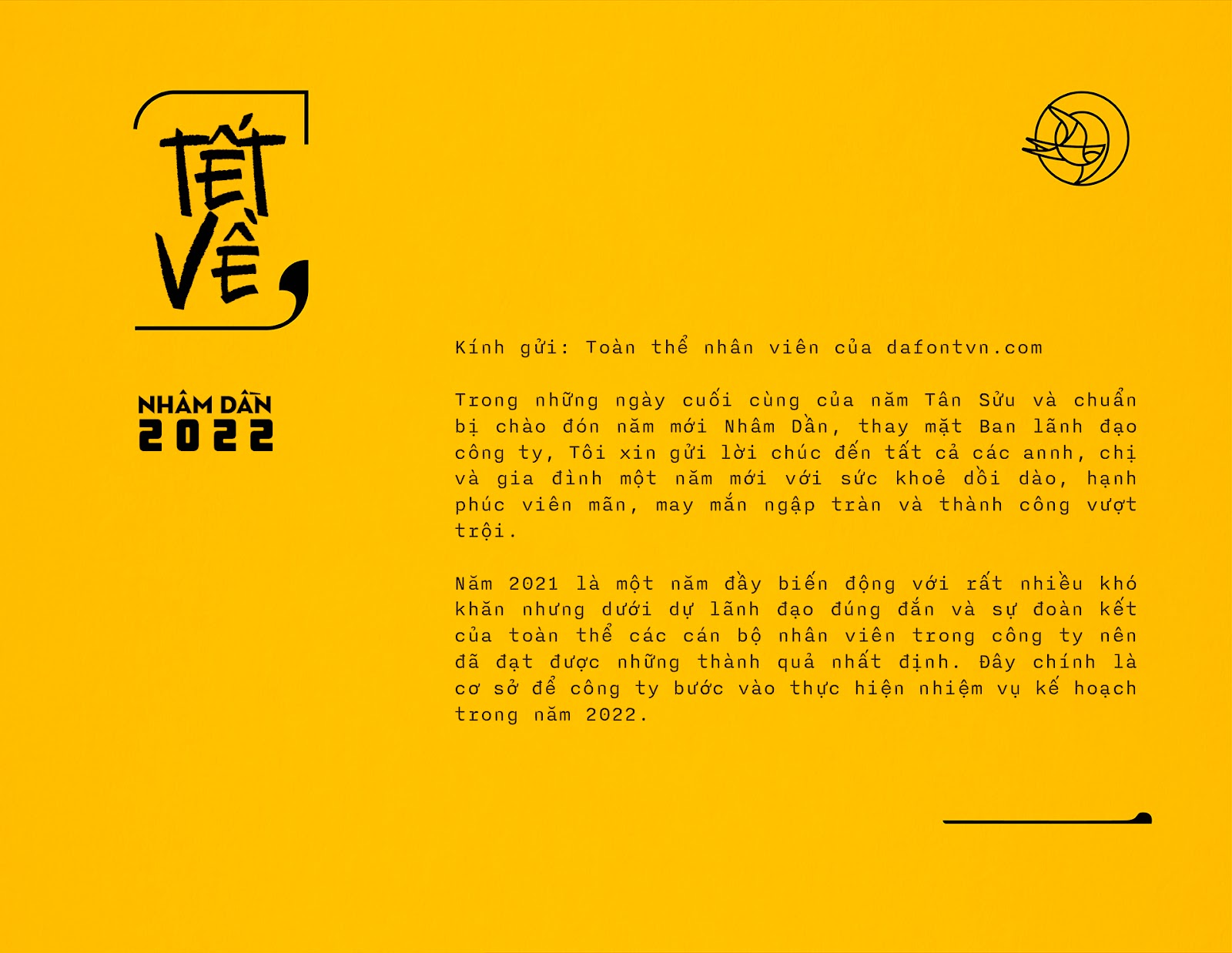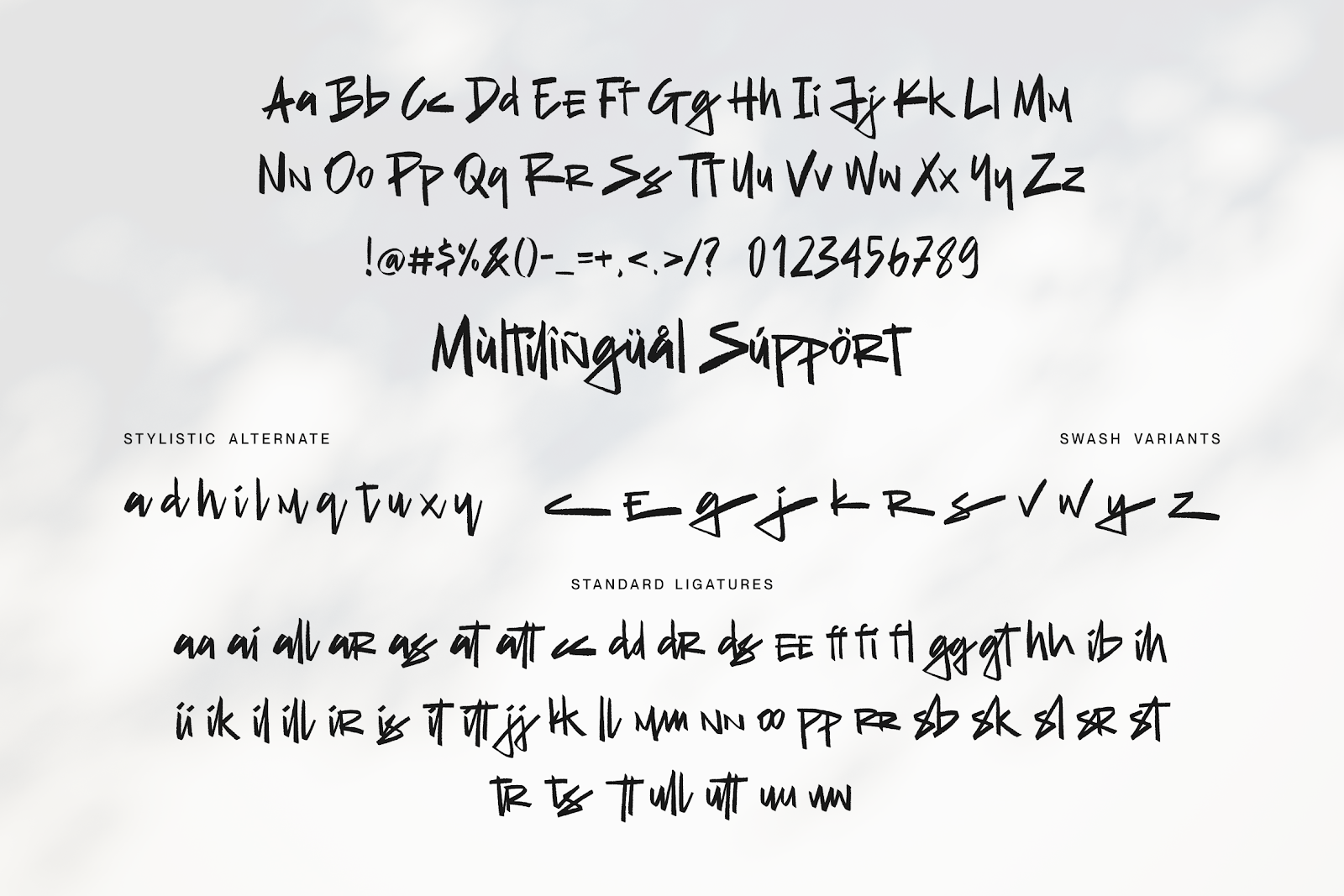
Font The Old Falcons Việt Hóa – Phông viết tay
Font The Old Falcons Việt Hóa – Phông chữ viết tay hoàn hảo cho các dự án xây dựng thương hiệu, megazine, mạng xã hội, thiệp mời… Với các nét chữ được thiết kế ấn tượng đem lại cảm giác giống như chữ viết tay thật. Việt hóa bởi 1314.